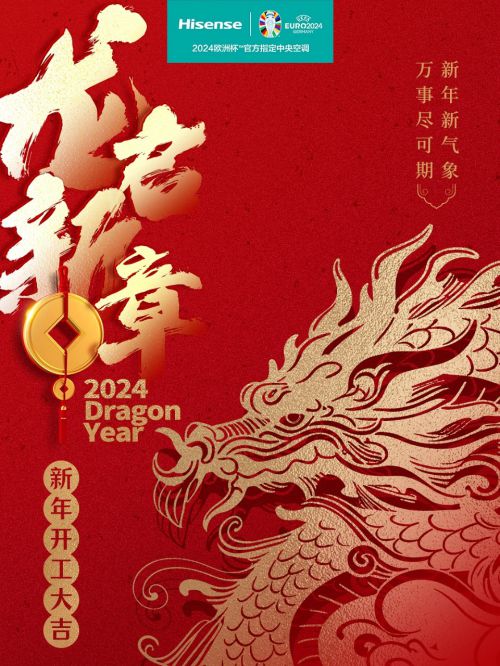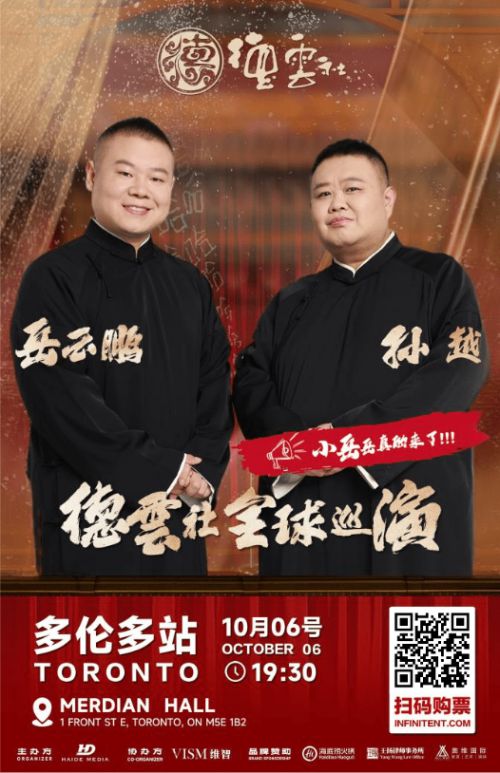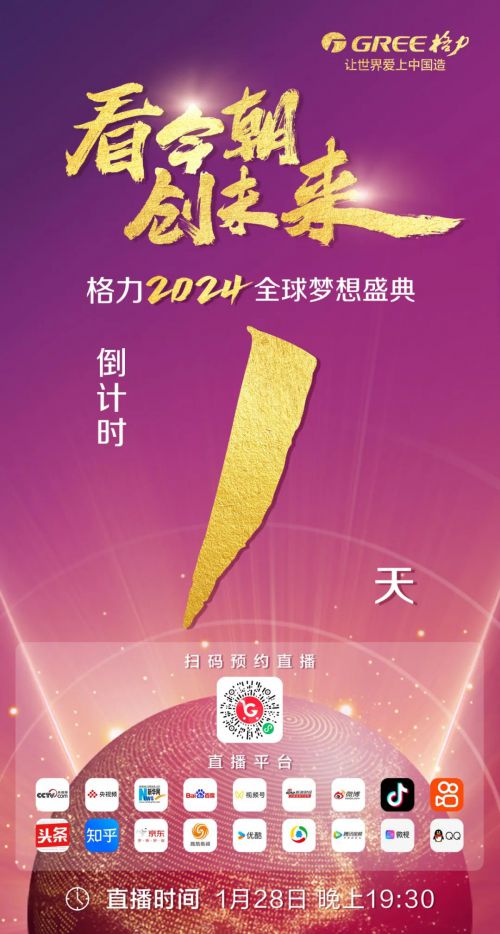
点字龙飞行书
点字龙飞行书保留了几乎所有粗糙的墨迹与飞白,以及粗细、干湿的碰撞,张力与美感并存。它不规则的形态,天马行空,无拘无束。当笔墨落下,让人忘记了世间所有的善书大家。点字龙飞行书不局限于各种形式的笔法,也无心玩弄技巧,使字体表达当下最强烈的情绪,感受到笔墨躁动于字体的每一个角落。摈弃陈规,彰显个性。